可以免费商用的可爱字体下载,10款推荐
站酷快乐体
原生手写可爱字体,全部笔画做圆角处理,字形宽松柔和,没有尖锐棱角,手写笔触自然松弛,不会出现过度花哨的装饰,整体氛围轻松治愈,字重均匀,长段落排版也不会拥挤杂乱,授权清晰,仅需简单标注来源即可商用,无额外费用。
适用场景:奶茶甜品店海报、儿童手工兴趣班宣传、宠物账号短视频字幕、零食电商主图标题、亲子活动 PPT、文创手作包装文案。
我平时做辅食店铺详情页标题,基本优先用这款,柔和的字形搭配浅色系背景,整体画面亲和力很强。
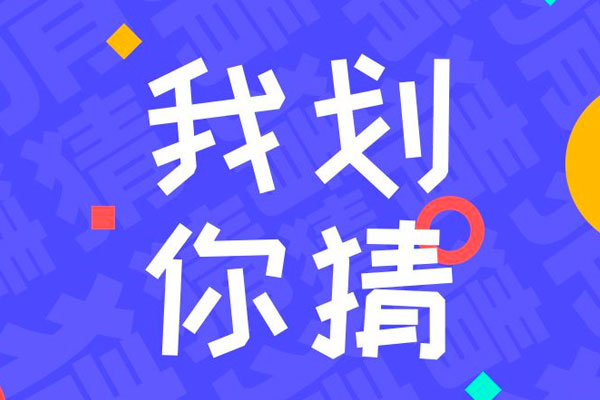
字魂扁桃体
开源免费商用手写体,笔画带有轻微手写粗细变化,字形圆润偏软萌,介于规整字体和涂鸦字体中间,可读性优秀,屏幕端和纸质印刷都清晰,支持网页、小程序嵌入使用,无强制署名要求。
长期做自媒体字幕我更偏爱它,长时间观看不会视觉疲劳,可爱但不浮夸。
猫啃什锦黑
猫啃什锦黑是一款马克笔手绘风格,笔画活泼有趣,圆润可爱的字体。是基于日本字体改造而成的中文手绘风格字体,补充了简体字并对部分汉字字形进行了优化。
做节日海报或者儿童产品包装的时候,这款字体能让画面活泼不少。
荆南麦圆体
荆南麦圆体是一款萌系可爱手写风格的字体,全字圆润无棱角,笔画饱满有质感。
适用场景: 软萌视觉表达的场景,儿童产品、手写风格设计等。每个笔画的粗细相同,两端圆润,可爱风格很突出。
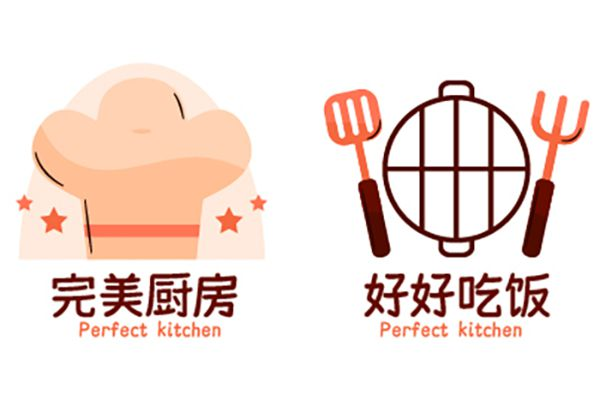
沐瑶软笔手写体
软毛笔质感可爱手写体,笔触轻柔圆润,没有生硬顿挫,整体温暖治愈,字形大小错落自然,自带温柔氛围感,开源授权支持全场景商用。适用场景:花店宣传、手作工作室 LOGO 小字、治愈系短视频封面、母婴育儿推文、礼物贺卡印刷文字。
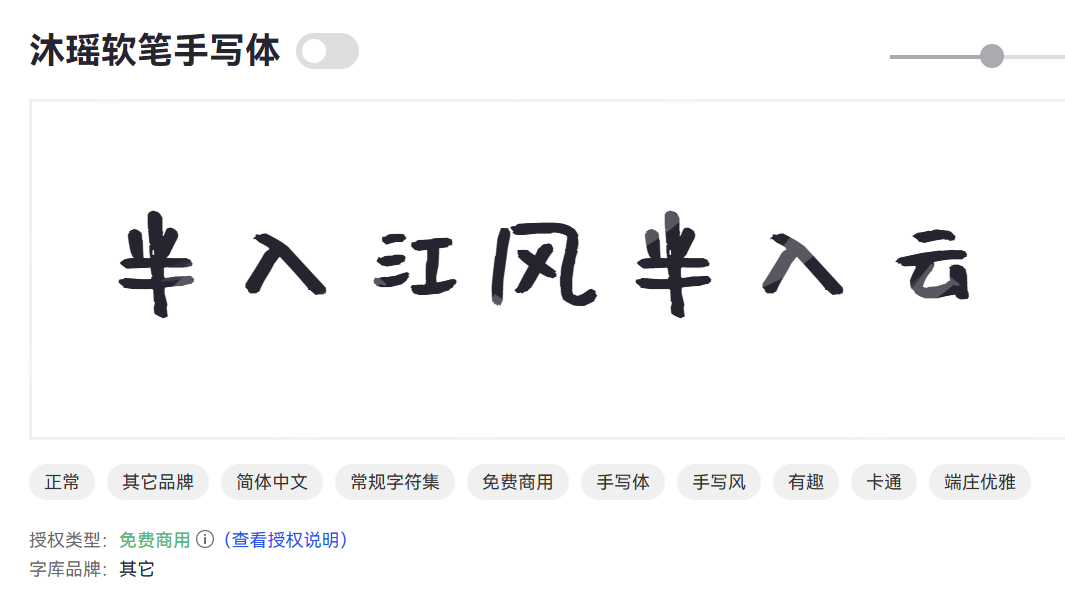
猫啃网糖圆体
猫啃网糖圆体是一款如糖果般甜美的圆体字,温和亲切,充满治愈感。采用扁宽结构设计,重心居中稳定,所有笔画均以圆润笔触呈现。
适用场景:儿童教育内容、品牌包装、社交媒体配图、电商促销广告等。
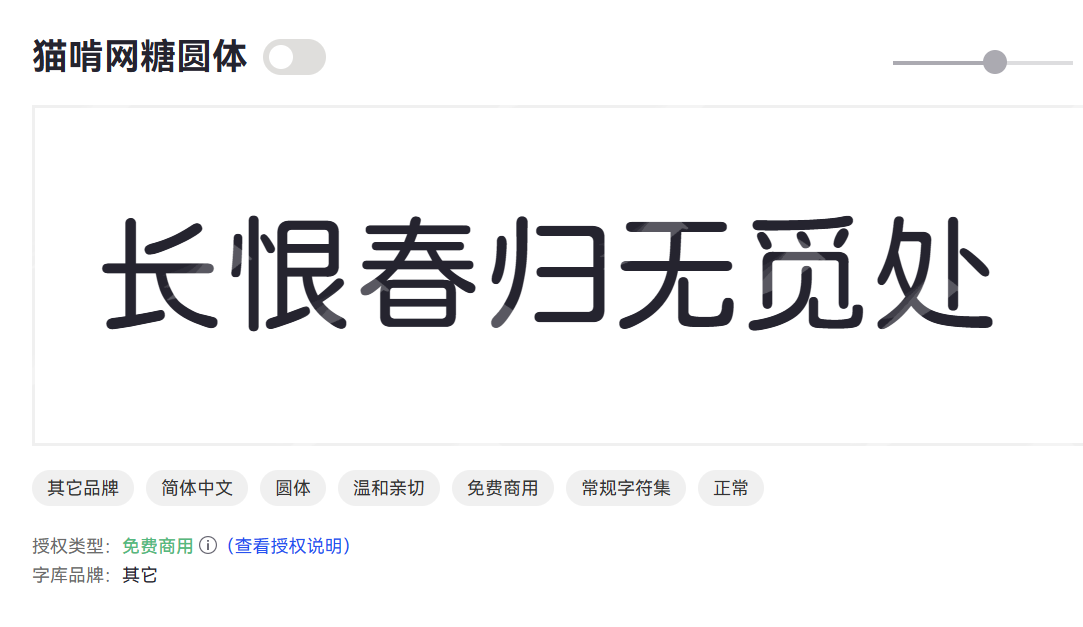
呆萌手写体
呆萌手写体是软萌治愈的趣味手写字体,笔画粗圆柔和,边角圆润无棱角,字形微微矮胖可爱,笔画错落随性。整体风格天真童趣,阅读清晰不杂乱,自带轻松可爱的氛围感。多用于儿童海报、零食包装、母婴图文、短视频字幕等年轻化设计。
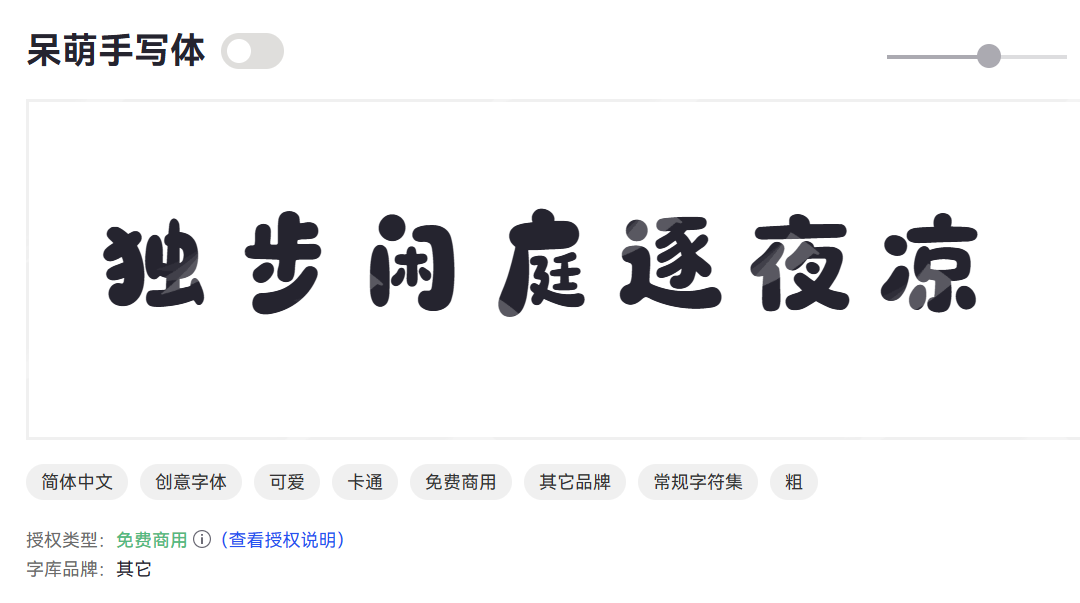
游趣体
游趣体是一款主打“趣味表达”的开源字体,字形带有轻微的倾斜和活泼的笔画细节,打破了传统字体的刻板感。它特别适合做短视频的封面花字或社交媒体上的趣味表情包配文。
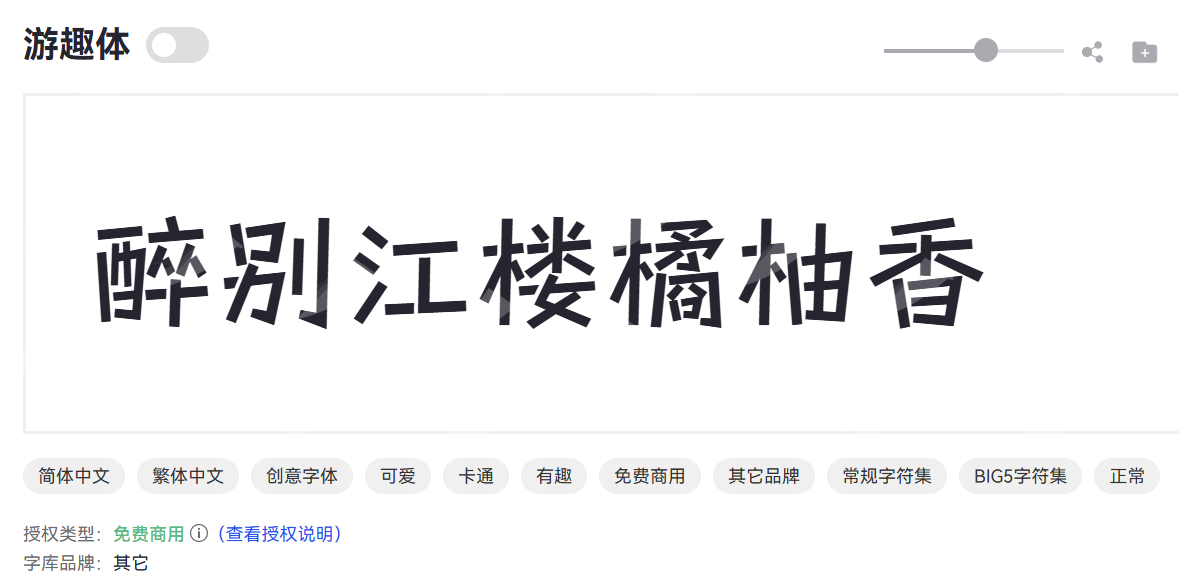
钉钉进步体
钉钉进步体非常具有科技活力与自然书写的美感。它整体带有7微斜的向前倾角,既可爱又不失专业感,非常适合做互联网产品的宣发海报或新媒体长图的标题。
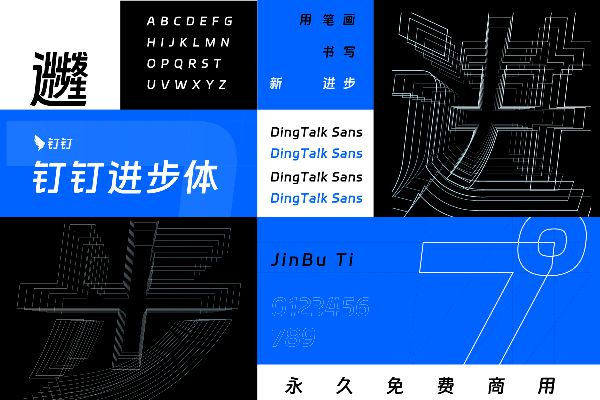
WestSide
WestSide 是充满美式街头风格的英文字体,笔画粗犷利落,线条硬朗富有张力,自带复古西海岸潮流质感。字母造型随性不羁,边角带有做旧质感,辨识度拉满,氛围感强烈。适配潮牌海报、服饰印花、街头文创、短视频封面等潮流设计。